#기업 전용서체란 무엇인가?
전용서체는 브랜드의 정체성과 이미지, 그리고 제품(서비스) 및 제작물에 이르기까지 하나의 폰트를 통해 일체화 함으로서 캠페인의 성과를 극대화하는 전략의 일환으로 개발됩니다.
이는, 소비자의 신뢰를 구축하고 강화하는데 기여하게 되고, 소비자 커뮤니케이션 과정에서 문자 정보를 통일된 서체로 제공하여 일관된 이미지를 지속적으로 제공하는 효과를 갖게 된 것 입니다. 이를 통해 소비자들은 글자체만으로 특정 브랜드를 인식할 수 있게 되고, 제품, 서비스, 제작물 등에 대한 안정감과 믿음을 주는 효과를 얻게 됩니다.
그리고, 로고, 제품, 서비스, 제작물 등에 사용한 폰트를 고객들도 무료로 사용할 수 있게 함으로서 일상 속에서 소비자들에게 브랜드에 대한 경험을 더 자주 하게 하는 역할을 합니다. 이를 통해 소비자와 브랜드의 유대감을 더 강해지는 효과를 거둘 수 있습니다.
RixFont와 함께 제작한 기업 전용서체 사례
#티몬, 고객 목소리에 귀 기울인 '티몬체'
티몬의「티몬체」(구명칭'몬소리체'/RixFont제작)는 몬소리 캠페인의 일환으로 제작되고 활용되었는데, 몬소리 캠페인은 소비자들이 힘들고 지칠 때 무심코 내는 웅얼거림으로, 티몬만이 알아들을 수 있는 고객의 목소리를 말합니다. 예를 들어 '모뒐퓟보코옱콜랐는데망햁'은 '모델핏보고 옷 골랐는데 망했다' 등으로 해석 되는거죠. 이는 고객과의 소통을 통해 소비자들 불만을 보다 잘 받아들여 고객만족도를 극대화하기 위한 캠페인으로, 이를 위해 유명 톱모델이 아닌 자사 캐릭터 '티모니'를 활용해 TV CF 영상을 제작했으며 친근하고도 일관된 이미지로 브랜드 캠페인을 진행했습니다.
그리고, 누구나 폰트를 자유롭게 사용할 수 있게 배포해 일상 속에서도 지속적으로 티몬을 상기시키는 효과를 거두고 있습니다.
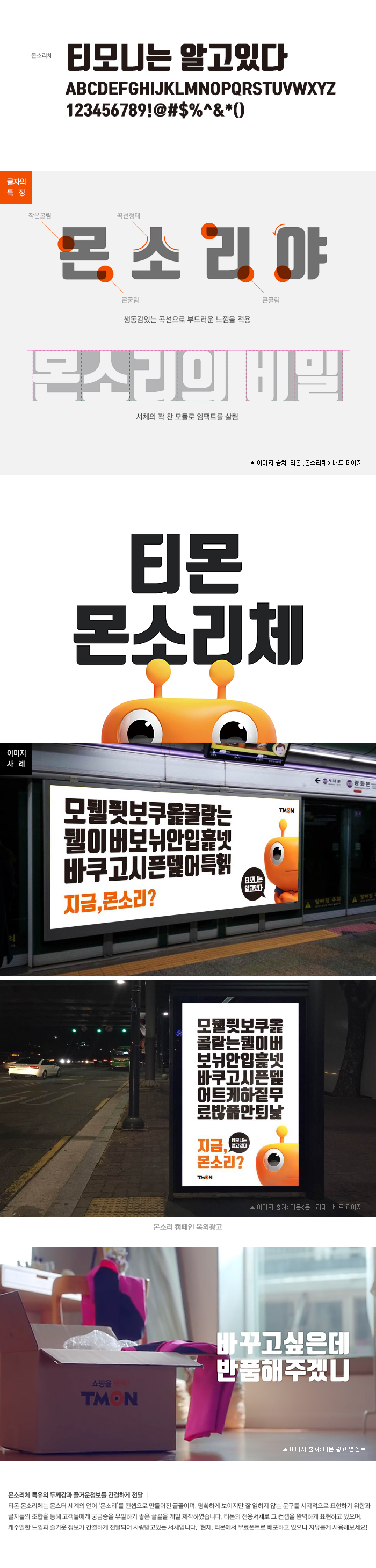
소셜커머스 시장이 경쟁이 치열한 상황에서 할인과 쇼핑 혜택만을 강조하는 캠페인을 탈피해 고객의 소리를 더 귀담아듣고, 고객의 입장에서 고민하고 있다는 티몬의 기업철학이 성공적으로 전달되고 있는 사례입니다.
#네이버 나눔글꼴 프로젝트
온라인 세상에 한글로 표현된 생각과 정보가 많아지길 바라며, 네이버가 시작한 한글 캠페인 "나눔글꼴 프로젝트"는 현재 가장 많이 사용되고 있는 무료서체 중 하나입니다.
RixFont는 네이버와 함께 나눔글꼴 프로젝트에 참여해 '나눔명조', '나눔바른고딕', 나눔옛한글'을 제작하였습니다.
나눔명조는 기존 명조체를 계승 발전시켜 획의 단순화 과정을 거치고 현대적 미감에 맞게 제작한 새로운 명조체로 개발되었습니다.
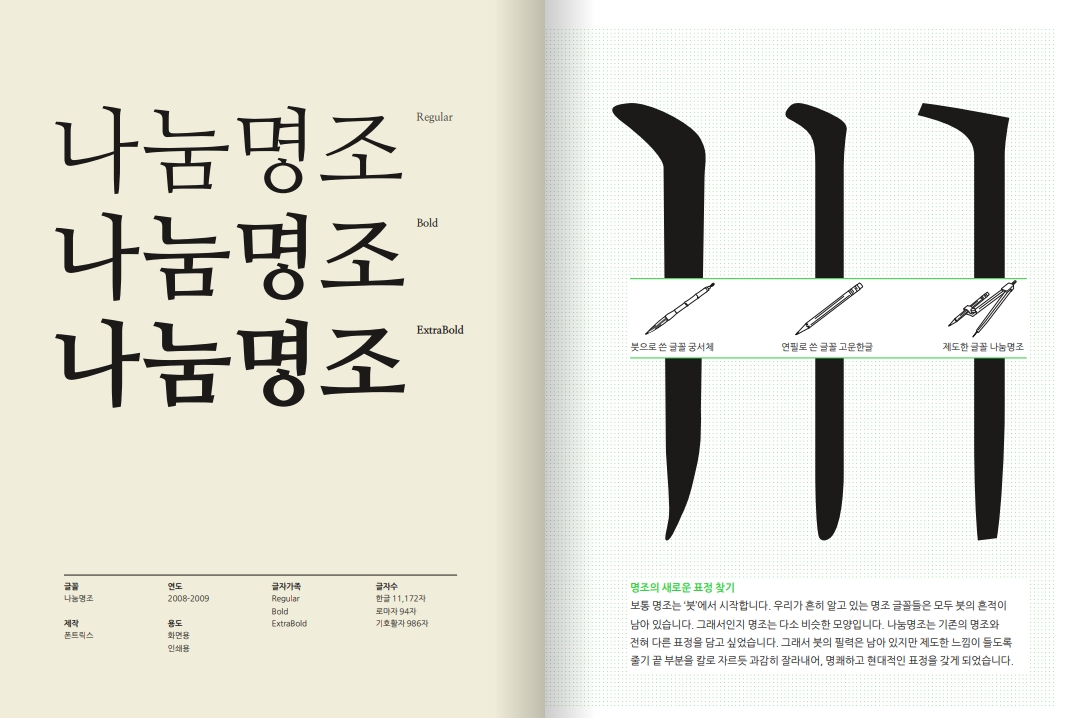
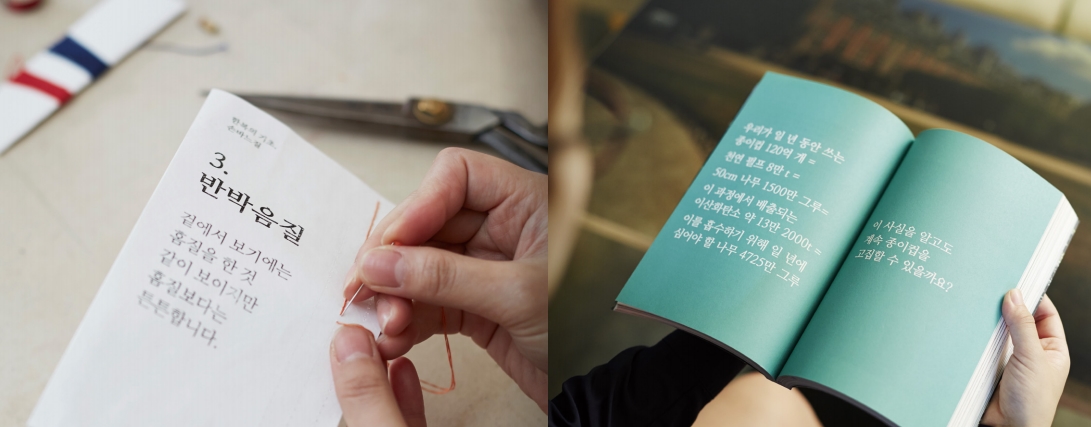
나눔바른고딕은 친근한 이미지와 어떠한 환경에도 잘 어울리며 오래 사용될 수 있는 모던한 스타일의 고품격 서체로 제작되었습니다.
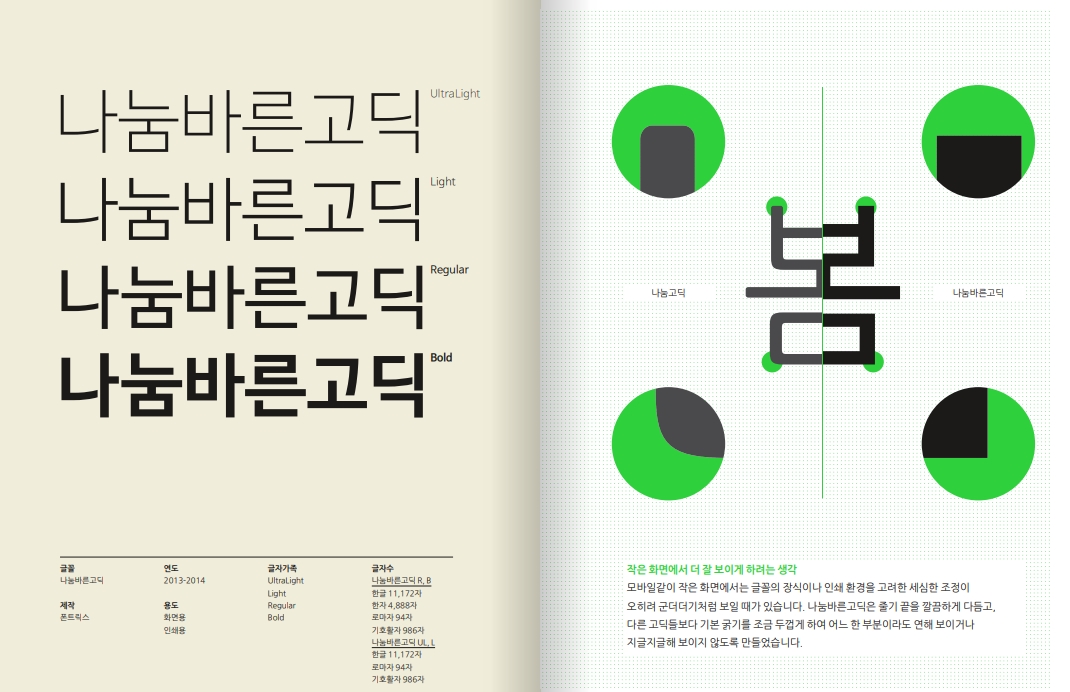
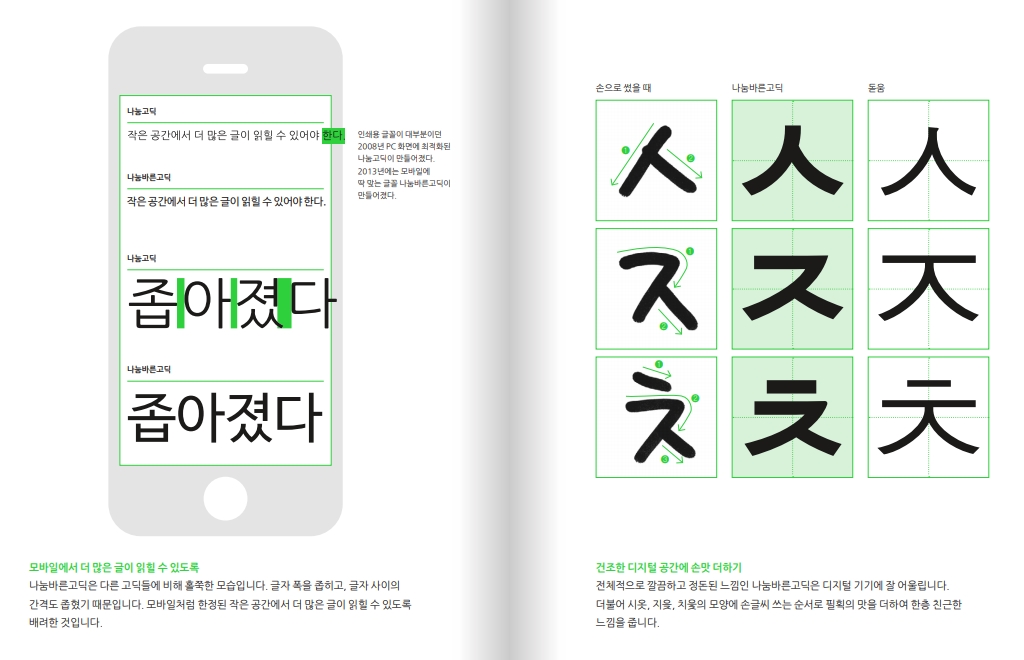
네이버는 지금도 한글한글 아름답게 캠페인을 통해 한글의 아름다움과 우수성을 알리는 캠페인을 지속적으로 진행하고 있으며, RixFont와도 협력 관계를 유지하고 있습니다.
#대기업의 전용서체 제작, 삼성의 '삼성원'서체
스타트업 기업뿐 아니라, 대기업에서도 전용서체를 제작하고 사용하는 사례들이 있습니다. 대표적으로 '삼성전자'의 「삼성원」(RixFont제작) 서체를 들 수 있습니다. 이는 소비자들에게 무료로 배포해 일체감을 주는 방식의 활용이 아니라, 자사 제품에 탑재하기 위해 제작된 서체 입니다. '삼성원'은 고딕의 노말함 속에 형태, 밸런스, 굵기, 모듈 등 완성도를 높이고 영문, 한문과의 조화도 균형 있게 제작해 모든 환경에서 최적화된 사용이 가능한 서체로 개발되었습니다. 삼성전자의 신제품이 나올 때마다 업그레이드가 되고, 모든 제품에서 사용 됩니다. 삼성 제품을 사용하는 소비자는 항상 동일한 서체를 보게 되고 제품에 대한 안정감을 유지시킬 수 있습니다. 가끔은 제품 성격에 맞는 새로운 서체가 개발되기도 하고, 자사의 글로벌에서 표준으로 사용되는 다국어 폰트를 직접 개발해 사용하기도 합니다.
그리고, 삼성만이 할 수 있는 한글의 아름다움을 전 세계에 알리는 마케팅 활동으로 대한민국 대표기업 이미지를 확고히 하고 있습니다.
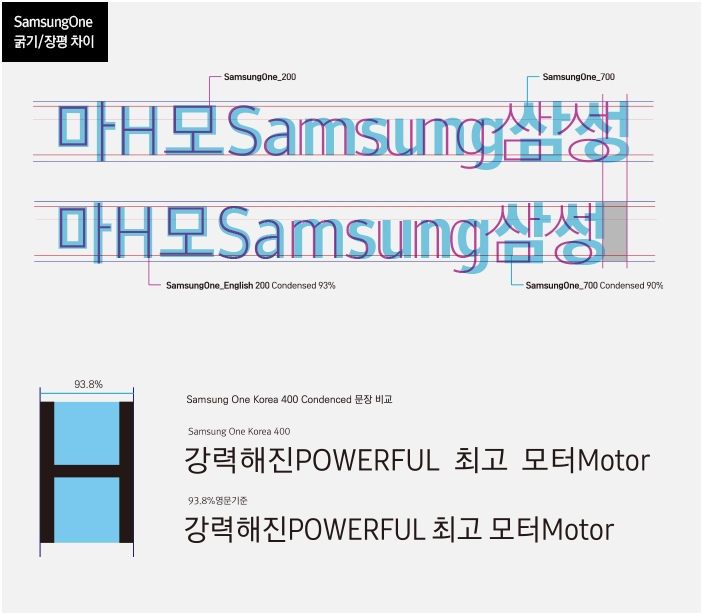
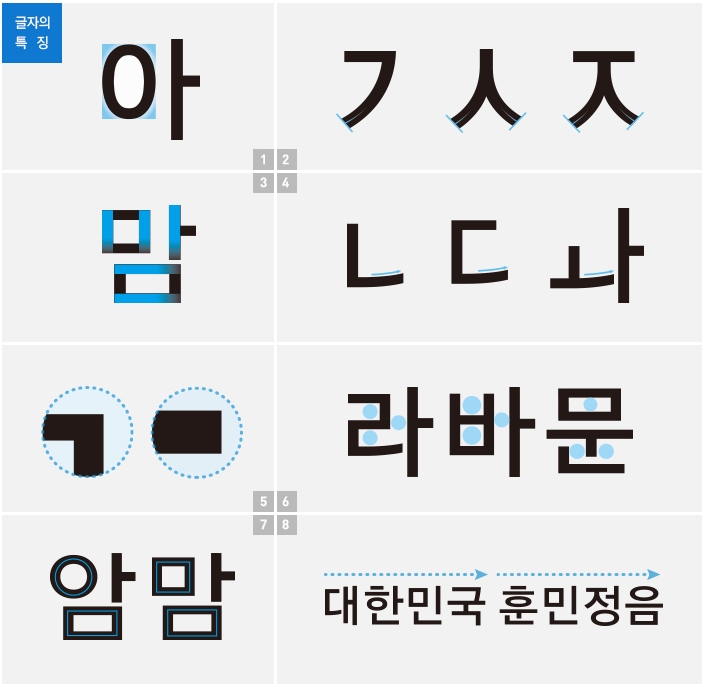
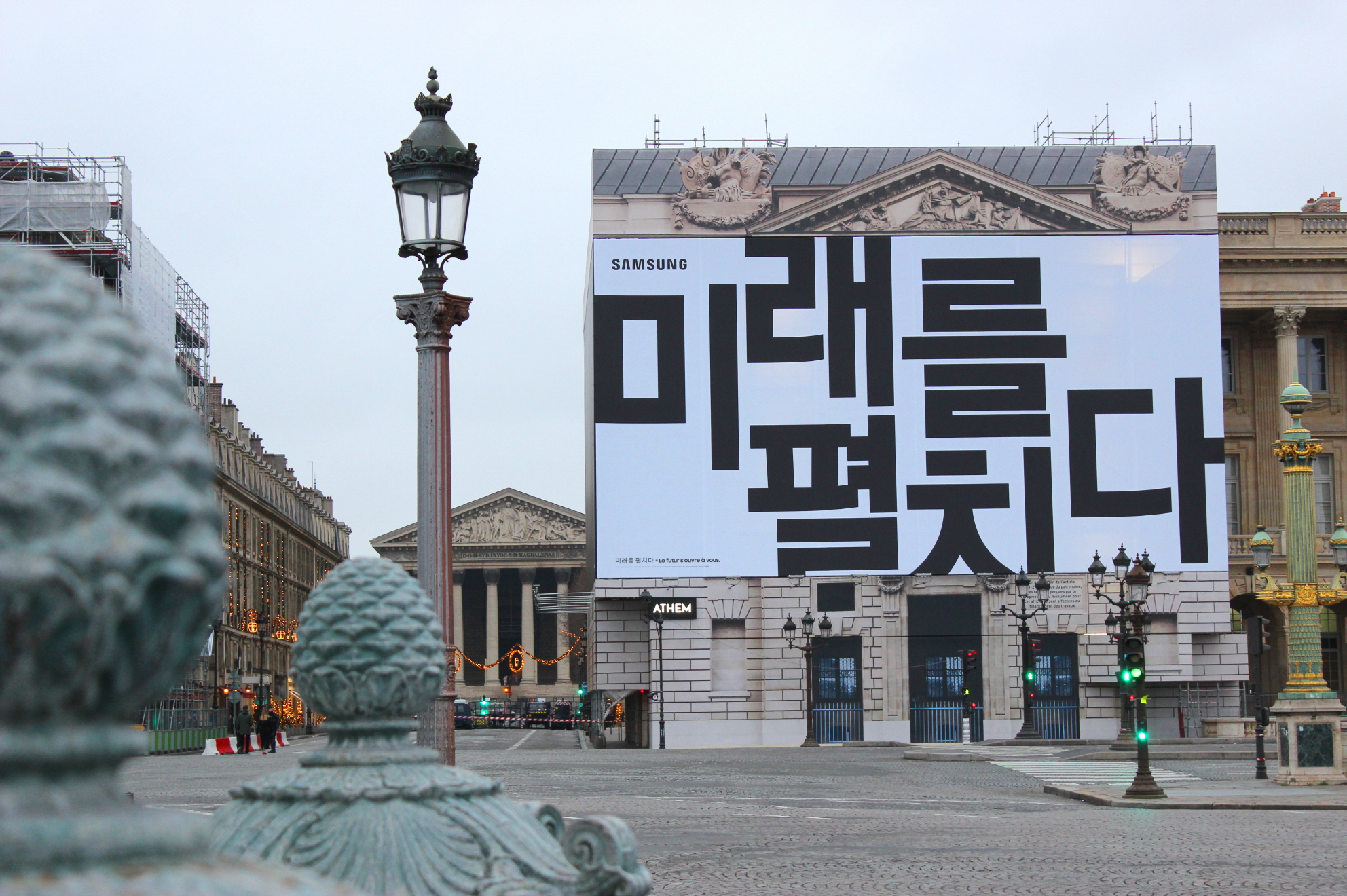
#MBC만의 색과 디자인을 담은, 'MBC새로움체'
이 외에 방송국에서도 전용서체 바람이 불고 있습니다. tvN의 '즐거운 이야기체'를 시작으로 최근 MBC는 「MBC새로움체」(RixFont제작)를 제작해 자사의 방송 프로그램에 활용하고 있습니다.새로움체는 MBC만의 정신과 그래픽 모티브의 특징을 담아 단단하고 안정적인 구조로 디자인된 방송용 전용서체 입니다.
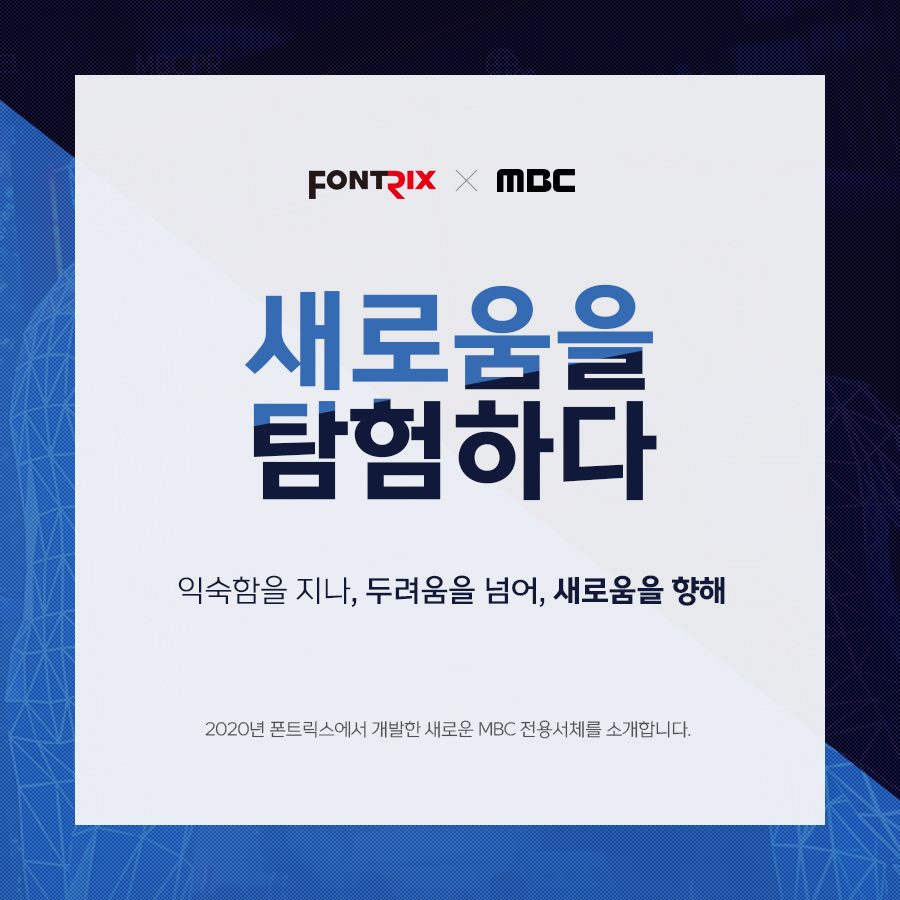
원래는 MBC 그래픽팀 디자인용으로 제작하였는데, 사내 반응이 좋아서 뉴스 자막에도 사용하게 되었습니다.
현재 다양한 보도, 교양 프로그램 및 예능, 드라마에서도 사용되는 것을 볼 수 있습니다.
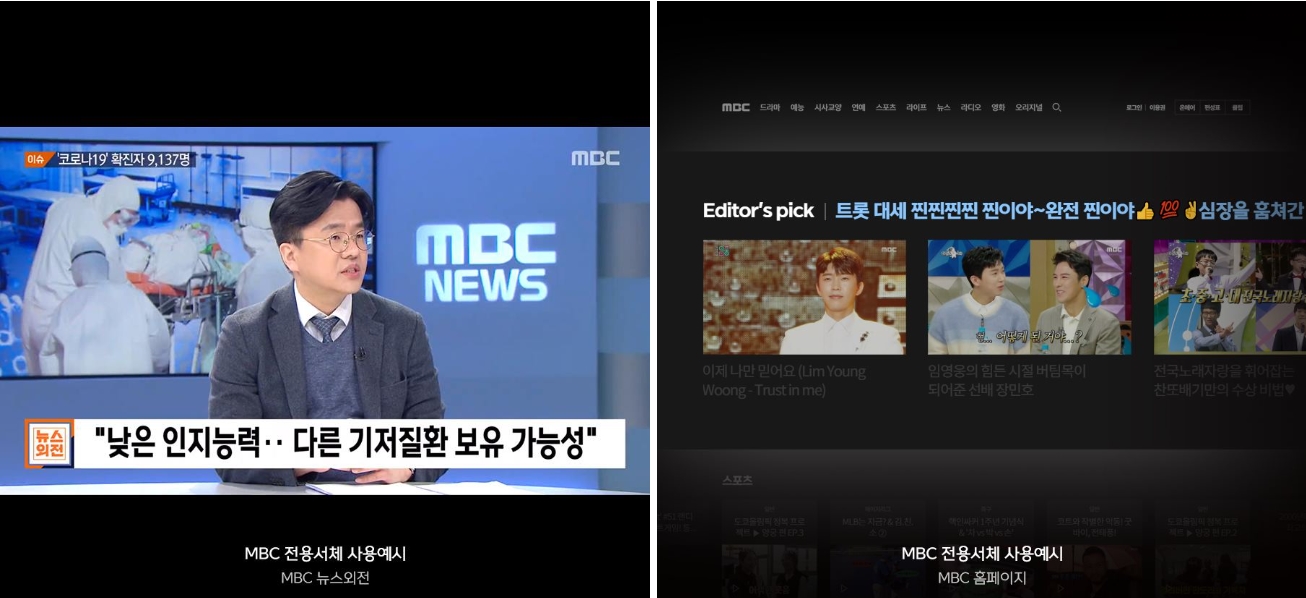
기업이든 지자체든 전용 서체를 무료로 배포하는 것 자체가 브랜딩이라 생각하면 틀린 생각입니다.
폰트를 활용한 자사의 이미지, 제품, 서비스, 제작물 그리고 소비자와의 유대감 형성까지 정교한 전략과 구체적인 실행 계획이 있어야 성공적인 브랜딩이 가능합니다. "서체를 제작해서 무료로 배포하면 사람들이 공짜니까 많이 쓸 거야"라는 생각으로 접근한다면 소비자들이 폰트는 사용할지 몰라도, 기업과 연계한 이미지를 떠올리거나 기업과의 유대감을 형성하지는 않을 것이기 때문입니다.